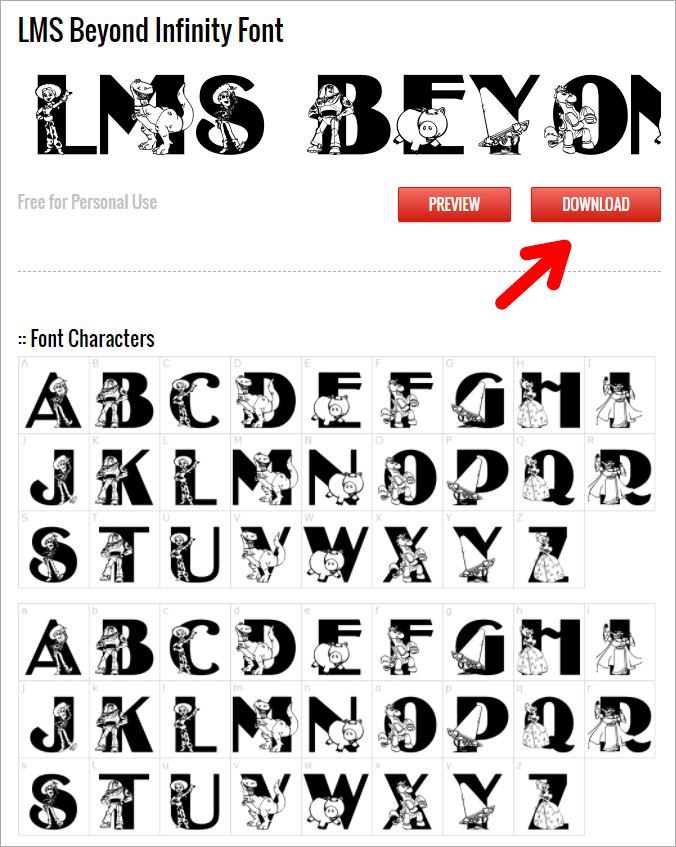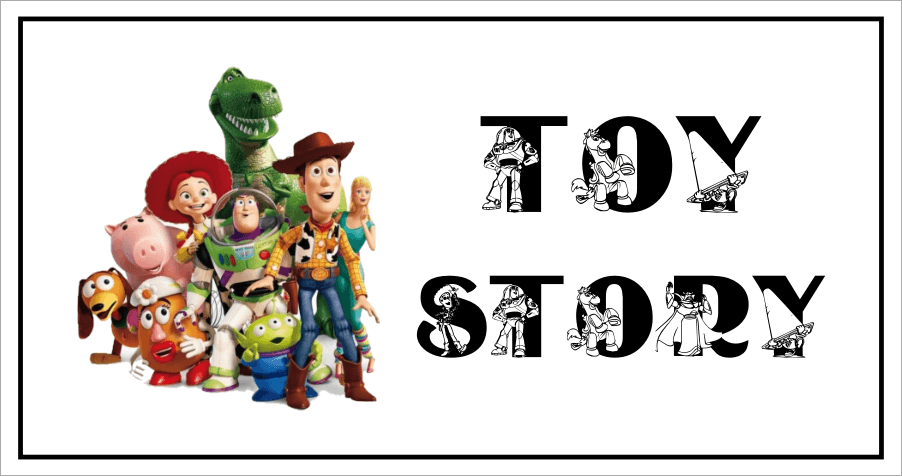
你也跟小編一樣是個玩具總動員的大粉絲嗎?那麼你一定會喜歡這個 LMS Beyond Infinity Font 玩具總動員英文字體!LMS Beyond Infinity Font 英文字體,是一個專門為喜愛玩具總動員中所設計的英文字體,每一個字母都會伴隨一個玩具總動員中的人物,像胡迪、巴斯光年、翠絲、三眼怪、火腿、抱抱龍、牧羊女、蛋頭夫婦等角色都有,且此英文字體完全免費供個人和商業使用,喜歡的朋友趕快來下載使用吧!更多好看的英文字體,可參考這篇:11 個設計師私藏英文字體!